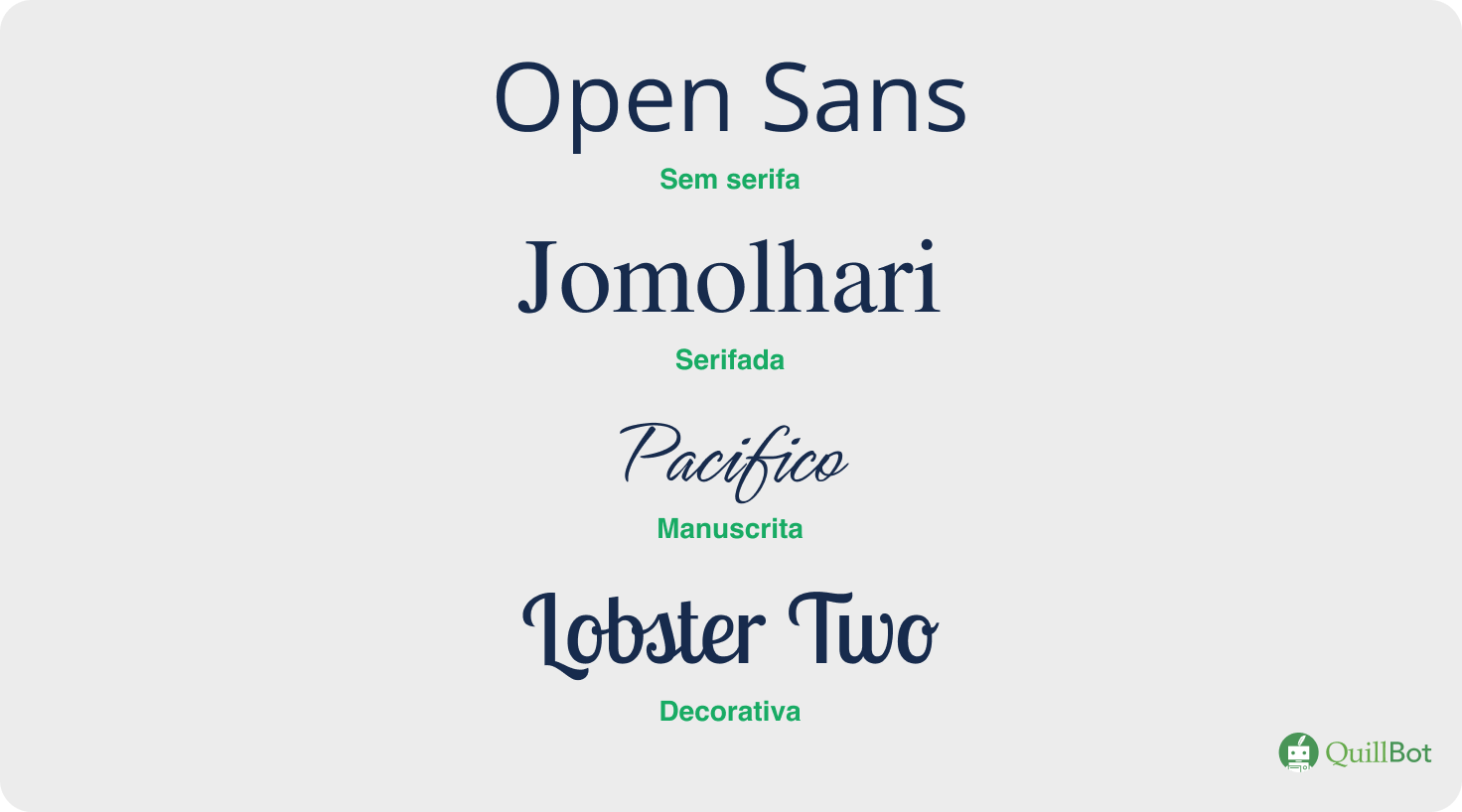
Tipos de letras | Exemplos e alfabetos
Tipos de letras são os estilos de escrita que comunicam o tom e a emoção do texto.
Tipos de letras também são utilizados para adequar o texto a um propósito específico, como um cartaz, um jornal ou um convite.
Exemplos de tipos de letras
Times New Roman: serifada, aparência clássica e formal, muito usada em livros, jornais, trabalhos acadêmicos e documentos formais.
Helvetica: sem serifa, moderna, neutra e equilibrada, comum em logos, marcas, design gráficos, aplicativos e sites.
Brush Script: manuscrita, fluida e elegante, muito utilizada em convites e cartões.
Impact: display, grossa, forte e chamativa, comum em títulos, memes, cartazes e anúncios.
Quais são os tipos de letras?
Os tipos de letras são os diferentes estilos de fontes que existem e são definidos por características principais da identidade de cada letra.
Eles se adequam a propósitos específicos de uso.
Para o design, há quatro principais tipos de letras:
A imagem é a demonstração dos quatro tipos de fonte: Sem serifa, com a fonte Open Sans; Serifada, com a fonte Jomolhari; Manuscrita, com a fonte Pacifico; e Decorativa, com a fonte Lobster Two.
Serifadas (serif)
Letras serifadas, ou serif, possuem pequenos traços ou “pezinhos” nas extremidades, chamados de serifas.
As serifas podem ser retas, arredondadas ou decorativas e dão um visual mais clássico.
São tradicionais e formais, além de facilitarem a leitura em textos longos impressos.
Letras serifadas são muito usadas em livros, jornais e documentos oficiais.
Letras serifadas: exemplos
Georgia: tem letras mais largas e espaçadas, já que foi criada para leitura em telas; é muito confortável para leitura digital; usada em blogs, sites e leituras em dispositivos.
Garamond: elegante e sofisticada, com traços finos e equilibrados; tem um estilo mais refinado; comum em livros de literatura, convites e design editorial.
Baskerville: tem alto contraste entre traços finos e grossos, dando uma aparência elegante e moderna; é muito legível; normalmente usada em revistas, apresentações sofisticadas e impressões de qualidade.
Playfair Display: tem estilo moderno com base clássica, apresentando muito contraste e sendo expressiva; é ideal para chamar atenção; muito utilizada em títulos, cabeçalhos, sites modernos e branding elegante.
Sem serifa (sans-serif)
Como o próprio nome diz, as letras sem serifa, ou sans-serif, são simples e retas, mais limpas e modernas, sem acabamento nas pontas.
Letras sem serifa dão um visual limpo e moderno, atribuindo uma identidade minimalista ao design do texto.
São fáceis de ler em telas, portanto são preferidas em ambientes digitais.
Letras sem serifa: exemplos
Arial: com visual simples e neutro, é fácil de ler e muito comum em sistemas de computador; seus usos mais frequentes são em documentos digitais, apresentações e textos em geral.
Roboto: é moderna e versátil, proporcionando boa leitura em diferentes tamanhos; foi criada para telas digitais; usada em aplicativos (especialmente Android), sites e interfaces digitais.
Open Sans: é muito legível, com letras abertas e claras que funcionam bem em telas pequenas; muito utilizada em sites, blogs, interfaces web e conteúdo online.
Montserrat: com visual marcante, moderno e geométrico, é ótima para dar destaque; é comum em títulos, cabeçalhos, redes sociais, pela sua capacidade de atribuir um design moderno ao texto.
Manuscritas (script)
Letras manuscritas, também chamadas de script, são fontes que imitam a escrita feita à mão, como se tivessem sido desenhadas com caneta, lápis ou pincel.
Têm um estilo mais orgânico e natural, incluindo linhas que alternam de espessura, fina e grossa.
Letras manuscritas têm personalidade forte e podem atribuir identidade elegante, informal ou artística ao visual do texto.
Letras manuscritas: exemplos
Pacifico: é alegre e descontraída, com letras arredondadas e estilo amigável; é muito usada em redes sociais, logos informais e projetos criativos.
Dancing Script: tem movimento fluido e boa legibilidade para uma letra manuscrita; é elegante e leve; comum em convites de casamento, cartões e textos decorativos.
Great Vibes: inspirada na caligrafia clássica, é muito elegante e sofisticada, com traços finos e delicados; usada em convites formais, branding elegante e design de luxo.
Lobster: tem estilo de script moderno com boa visibilidade; é forte e marcante; comum em logos, títulos e posts de redes sociais.
Dica
Em geral, letras manuscritas ou cursivas não são ideias para textos longos porque cansam a leitura.
Display (decorativas)
Letras de display são letras criadas para impactar visualmente.
Têm estilos variados, grossas, finas, desenhadas, artísticas, e podem ser muito diferentes umas das outras.
Fonte é um tipo específico de letra, em geral, um arquivo digital.